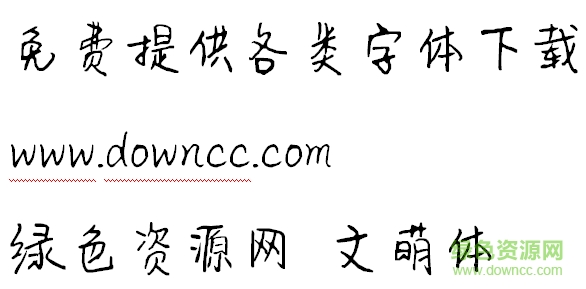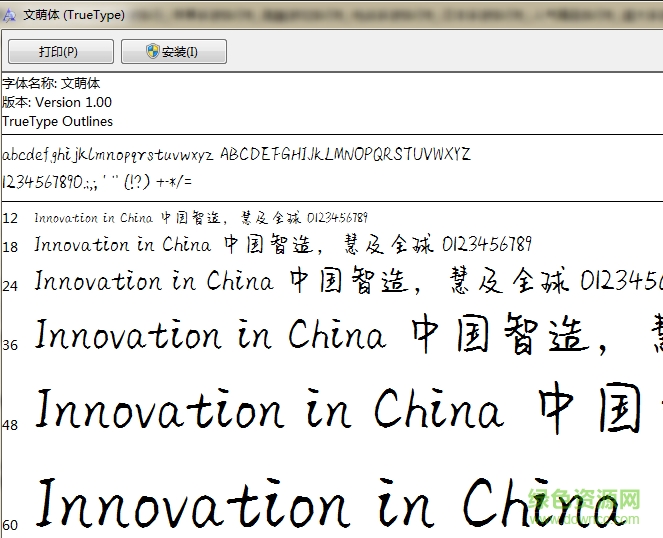
文萌體字體ttf是一款十分精美字體樣式,讓你在各種行業(yè)中都能夠盡情使用,同時(shí)獲得不錯的展示效果,能夠運(yùn)用到藝術(shù)創(chuàng)作以及影視,動漫作品中的字幕當(dāng)中,用戶十分廣泛!
這是一款眾多用戶都需要的經(jīng)典字體,能夠?yàn)槟銕硪庀氩坏降男Ч?,為你的作品增添更多光彩?/p>